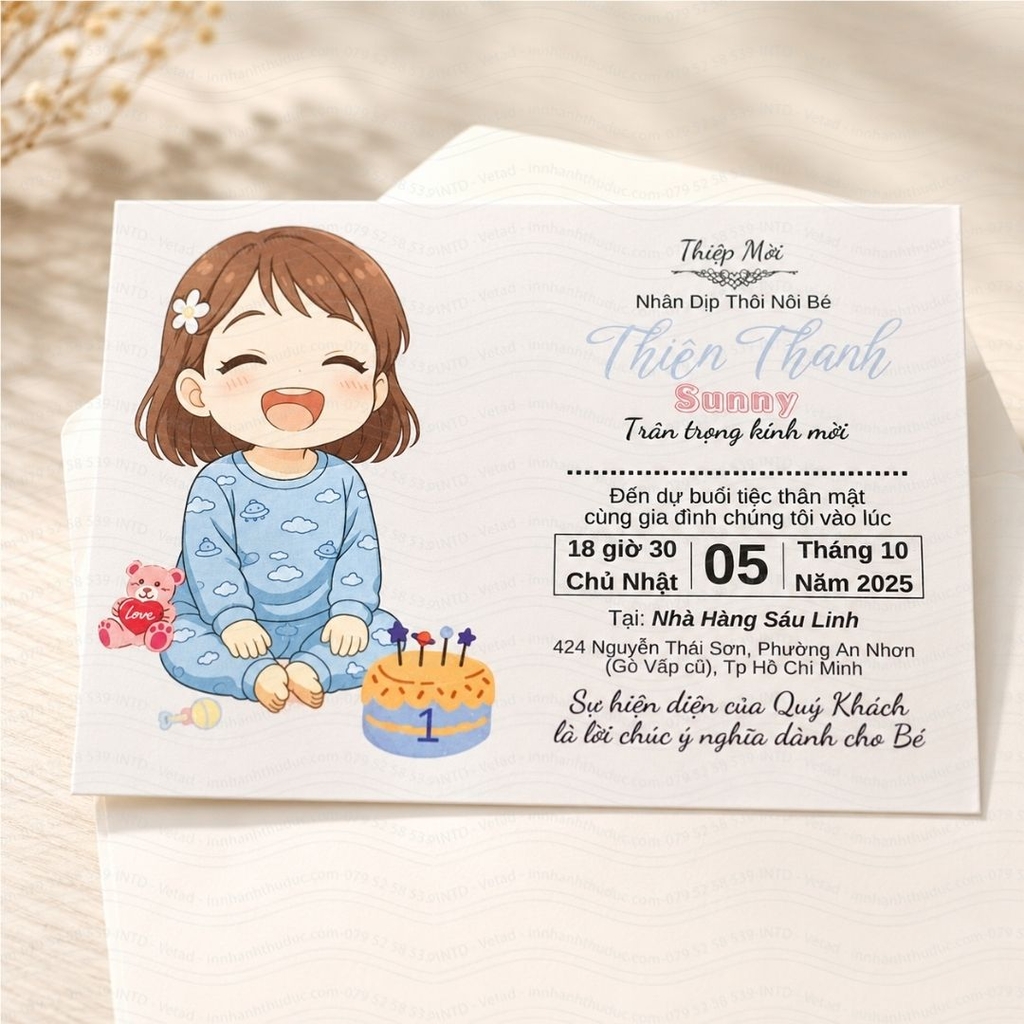
Top 10+ Font Chữ Việt Hóa Viết Tay Tuyệt Đẹp Dành Cho Thiệp Thôi Nôi
Một tấm thiệp mời hoàn hảo không chỉ cần hình ảnh đẹp, bố cục hài hòa mà còn phụ thuộc rất lớn vào nghệ thuật sử dụng kiểu chữ (Typography). Trong đó, các font chữ Việt hóa viết tay luôn là "vũ khí bí mật" giúp thiết kế trở nên mềm mại, sang trọng và mang đậm dấu ấn cá nhân.
Nếu bạn đang tự tay thiết kế thiệp mời thôi nôi cho bé, thiệp sinh nhật hay thiệp sự kiện nhưng chưa tìm được kiểu chữ ưng ý, hãy khám phá ngay bộ sưu tập 10+ font chữ viết tay tuyệt đẹp đã được Việt hóa hoàn chỉnh dưới đây!
1. Tại Sao Nên Dùng Font Viết Tay Cho Thiệp Mời?
Khác với các phông chữ có chân (Serif) hay không chân (Sans-serif) mang vẻ cứng cáp, nghiêm túc, font chữ viết tay (Script/Handwriting) mô phỏng lại những đường nét uốn lượn tự nhiên của bút mực, cọ vẽ.
Việc sử dụng font viết tay trên thiệp mời mang lại những hiệu ứng tuyệt vời:
Tạo sự thân mật: Mang lại cảm giác như tấm thiệp được nắn nót viết tay gửi riêng cho từng vị khách.
Điểm nhấn nghệ thuật: Rất thích hợp để làm nổi bật tên nhân vật chính (Tên em bé, cô dâu chú rể) hoặc các tiêu đề lớn như "Thiệp Mời", "Thân Mời".
Phù hợp nhiều phong cách: Từ phong cách hoàng gia sang trọng (Classic), mộc mạc (Rustic/Vintage) đến sự ngộ nghĩnh, đáng yêu cho tiệc trẻ em.
2. Top 10+ Font Chữ Việt Hóa Viết Tay "Đỉnh" Nhất Hiện Nay
Dưới đây là các bộ font đã được Việt hóa chuẩn dấu, không bị lỗi font khi gõ tiếng Việt, được các Designer tại xưởng in cực kỳ ưa chuộng:
Nhóm Font Sang Trọng, Cổ Điển (Dành cho thiệp cưới, sự kiện VIP)
UVF Aphrodite Pro: Nét chữ thanh mảnh, uốn lượn bay bổng, vô cùng lãng mạn và quý phái.
SVN-The Carpenter: Mang phong cách calligraphy sắc nét, độ dày mỏng linh hoạt, tạo sự sang trọng tuyệt đối.
UTM Yves Bow: Nét chữ cổ điển, đều đặn, rất dễ đọc nhưng vẫn giữ được sự mềm mại cần thiết.
iCiel Blooming Elegant: Phông chữ toát lên sự thanh lịch, hiện đại, thường xuyên xuất hiện trên các mẫu thiệp cao cấp.
Nhóm Font Ngộ Nghĩnh, Đáng Yêu (Dành cho thiệp thôi nôi, sinh nhật bé)
SVN-Hollie Script: Nét chữ tròn trịa, hơi có độ nghiêng nhẹ, vô cùng dễ thương và thân thiện.
iCiel Ciao Bella: Vui tươi, nhí nhảnh với các nét cọ tự nhiên, cực kỳ hợp với các concept thiệp thôi nôi có hình chibi.
HL Brush: Phong cách chữ cọ cọ quét (brush) mạnh mẽ nhưng phá cách, tạo điểm nhấn lạ mắt cho thiệp tiệc.
UTM Sloop: Uốn lượn nhiều nhưng các nét chữ khá to và rõ ràng, phù hợp làm tên tiêu đề nổi bật.
Nhóm Font Tự Nhiên, Hiện Đại (Minimalism / Rustic)
SVN-Bakersville: Giống như nét bút bi viết vội nhưng rất có gu, mang lại cảm giác mộc mạc, gần gũi.
Dancing Script (Google Font): Mẫu font quốc dân, nét nghiêng tự nhiên, linh hoạt và rất dễ sử dụng trên Canva.
Pacifico (Google Font): Nét chữ tròn, đậm đà, mang hơi hướng retro, hiện đại.
3. Lưu Ý Kỹ Thuật Khi Dùng Font Viết Tay Trong In Ấn
Một file thiết kế đẹp trên màn hình máy tính chưa chắc in ra đã hoàn hảo. Khi mang file đi in ấn thực tế, bạn cần lưu ý 3 nguyên tắc "sống còn" sau:
Chỉ dùng font viết tay cho Tiêu đề/Tên: Tuyệt đối không dùng font viết tay để gõ các đoạn văn bản dài hoặc thông tin nhỏ (như địa chỉ, ngày giờ tiệc). Các nét uốn lượn khi in nhỏ sẽ bị dính vào nhau, cực kỳ rối mắt và khó đọc. Hãy kết hợp (pair font) với một phông chữ nét thẳng, đơn giản (như Arial, Montserrat, UTM Avo) cho phần thông tin.
Cẩn thận với độ mỏng của nét chữ: Nếu nét font quá mảnh, khi in trên các loại giấy mỹ thuật có gân chìm, mực có thể bị đứt nét. Hãy thêm một chút viền (stroke) mỏng hoặc in đậm (bold) nếu cần thiết.